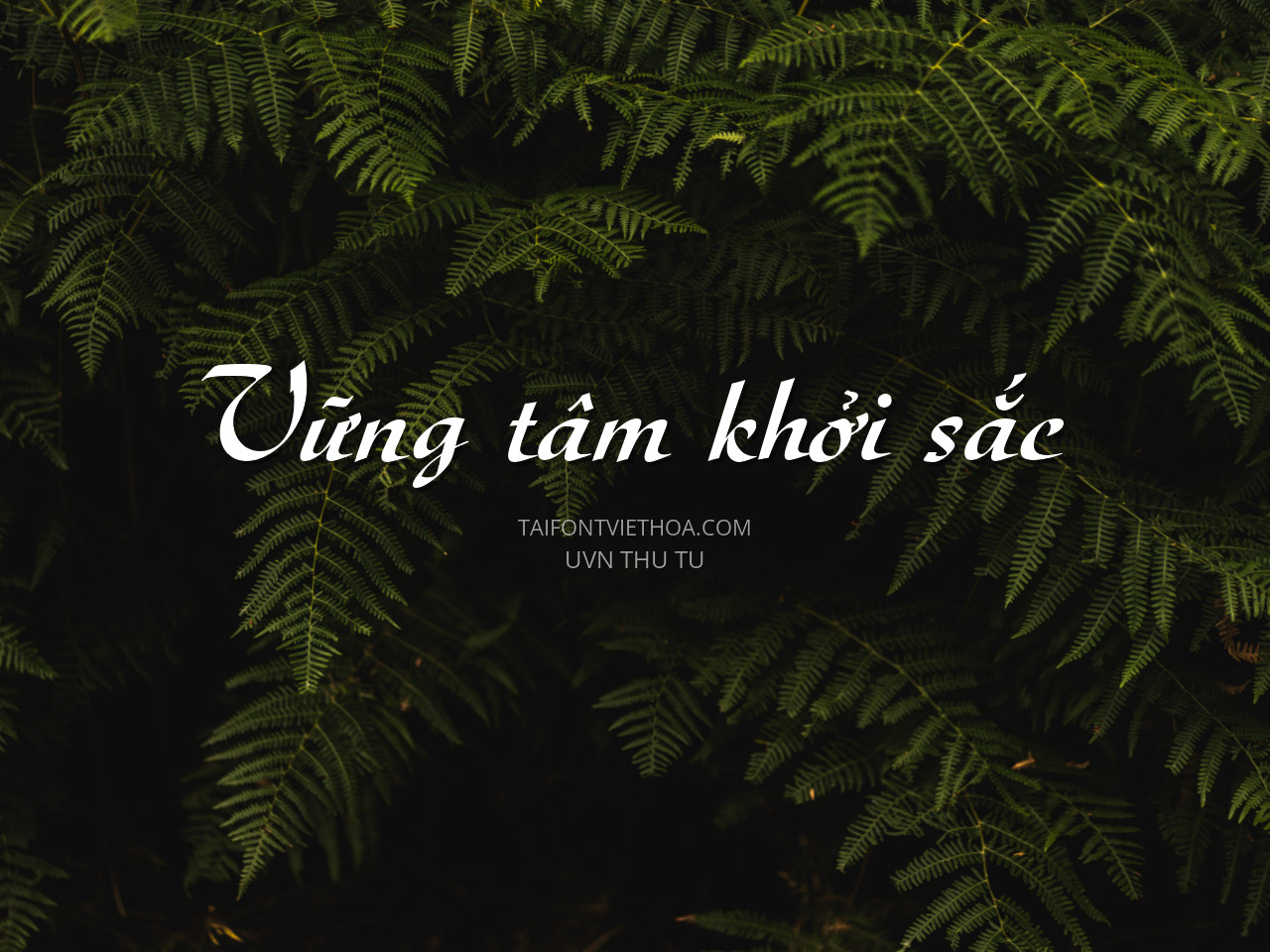
Font việt hóa UVN Thu Tu
Giới thiệu về font UVN Thu Tu
UVN Thu Tu là một bộ font mang phong cách nhẹ nhàng, gần gũi, gợi nhớ đến nét viết tay ngay ngắn của học sinh trong các buổi học đầu tuần. Cái tên “Thứ Tư” không chỉ đơn thuần là ngày giữa tuần mà còn thể hiện sự bình ổn, giản dị và đều đặn – như tinh thần font thể hiện qua từng đường nét. UVN Thu Tu được sưu tầm và chia sẻ bởi thành viên Font Chuẩn, và được taifontviethoa.com lựa chọn sử dụng trong nhiều dự án thiết kế mang tính giáo dục, học đường và truyền tải thông điệp mộc mạc, thân thiện với người đọc.
Đặc điểm thiết kế và ứng dụng của UVN Thu Tu
Font UVN Thu Tu có kiểu dáng gần giống chữ viết tay cơ bản, với các nét chữ mềm mại, đều nhau và dễ đọc. Cấu trúc chữ rõ ràng, có sự cân đối giữa các đường nét cong và thẳng, tạo nên sự ổn định và thân thiện trong thị giác. Font hỗ trợ tiếng Việt đầy đủ và phù hợp với nhiều hình thức trình bày truyền thống hoặc gần gũi.
Ứng dụng lý tưởng: bảng nội quy lớp học, tài liệu giảng dạy, slide giáo án, ấn phẩm giáo dục học sinh. Ngành nghề phù hợp: giáo dục, xuất bản sách học sinh, thiết kế học đường, tổ chức sự kiện liên quan đến văn hóa học thuật.